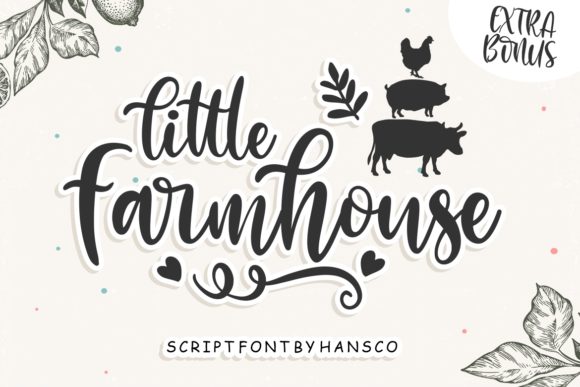
Little Farmhouse Font
Jika Anda mencari aset berkualitas tinggi seperti Little Farmhouse Font, paket premium ini adalah pilihan fantastis untuk proyek kreatif Anda.
Dibuat dengan presisi, Little Farmhouse Font menyediakan vektor yang bersih, tipografi yang halus, serta lisensi komersial untuk ketenangan pikiran Anda.
Sangat cocok bagi para crafter, desainer grafis, dan pemilik usaha kecil yang ingin menambahkan sentuhan profesional pada produk mereka.
Tips Ahli: Padukan elemen-elemen ini dengan font pendamping untuk menciptakan desain unik dan menarik yang menonjol di pasaran.